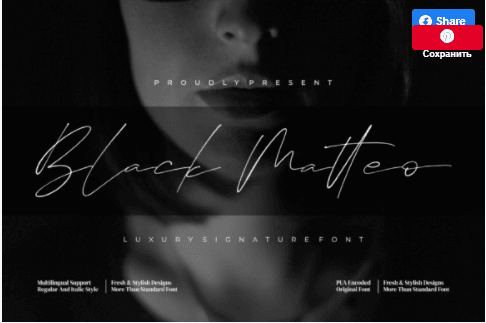
Black Matteo Font
Black Matteo - стильный и нежный шрифт. У него чистая, тонкая и гладкая атмосфера, и он станет хитом для любого дизайна, к которому вы хотите добавить его. Black Matteo закодирован в кодировке PUA, что означает, что вы можете легко получить доступ ко всем глифам и росчеркам!